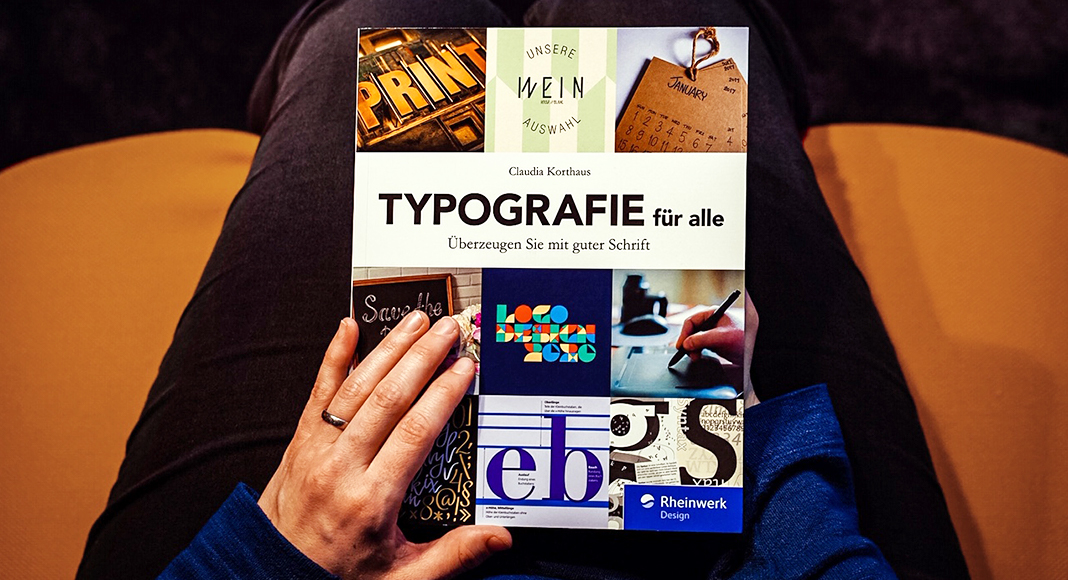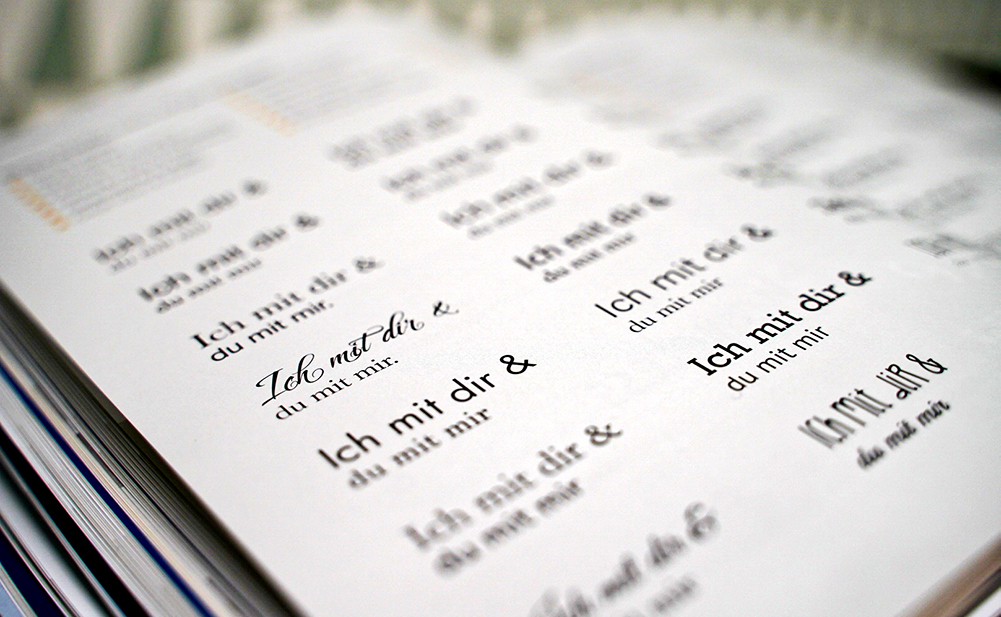
Wir haben das Buch „Typografie für alle – Überzeugen Sie mit guter Schrift“ von Claudia Korthaus gelesen und können es Ihnen auf jeden Fall ans Herz legen. Damit Sie sich einen Überblick verschaffen können, stellen wir Ihnen das Buch im Folgenden vor.
Wenn Sie für die Gestaltung von Drucksachen, Werbemitteln und anderen Designs eine überzeugende Typografie suchen, finden Sie in diesem Ratgeber Antworten. Die Autorin richtet sich mit ihren Tipps bewusst an alle, die im Alltag mit Schrift zu tun, aber Design nicht als Handwerk gelernt haben.
Claudia Korthaus arbeitet als selbstständige Grafikdesignerin, hat bereits mehrere Bücher zum Thema Typografie und Design veröffentlicht und schreibt regelmäßig Fachartikel für das ONLINEPRINTERS-Magazin.
Buchvorstellung: „Typografie für alle“
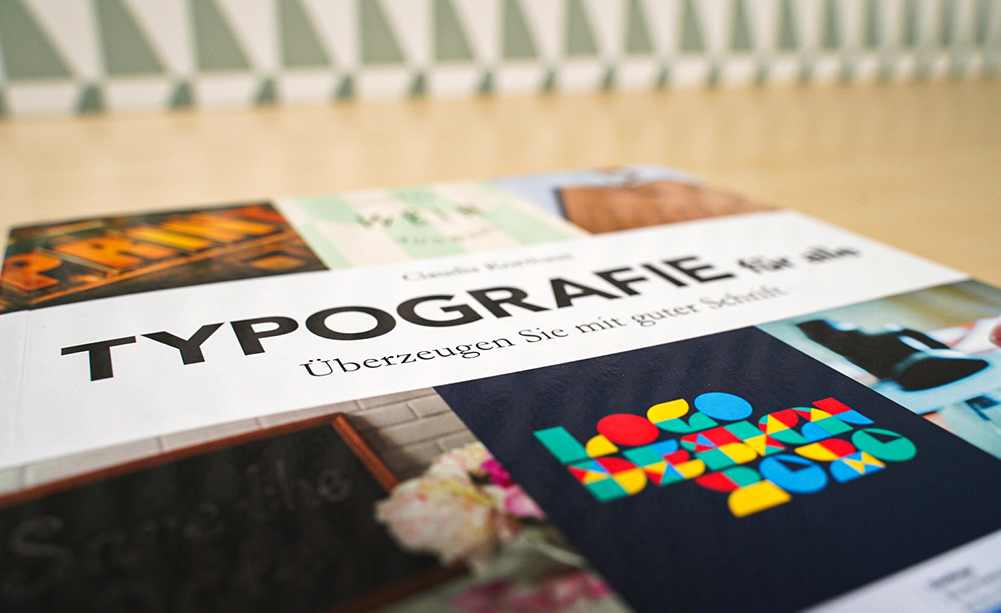
Auf den Innenseiten des Umschlags wird der Leser mit anschaulichen Begriffserklärungen begrüßt. Auch im Rest des Buches gibt es auf den in einem übersichtlichen Layout gestalteten Seiten immer wieder Definitionen zu entdecken. Das erleichtert das Lesen ungemein. Der Text selbst ist das Gegenteil von einer Bleiwüste und weist eine ansprechende Gestaltung auf. Er ist unterbrochen von zusammengefassten Erläuterungen sowie grau hinterlegten Absätzen mit zahlreichen Beispielen oder wissenswerten Exkursen.
„Typografie für alle“ ist in zwei große Teile unterteilt: Theorie und Praxis. Wobei diese Kategorisierung nicht ganz den Kern erfasst, denn auch in der ersten Hälfte finden sich Beispiele aus der Praxis. In den ersten drei Kapiteln erklärt Claudia Korthaus, warum Schriften wichtig sind. Im Zweiten gibt sie einen rechtlichen Abriss über Lizenzen und im Dritten werden Schriftwahl und -Kombinationen zum Thema. In Kapitel vier befasst sich die Designerin mit konkreten Gestaltungsbeispielen und gibt Tipps für den guten Einsatz von Schriften.
Kapitel 1: Die Bedeutung von Typografie
Gute Typografie ist wichtig „für jeden, der über die Schrift einen Inhalt transportieren und diesen zudem noch verständlich darstellen möchte“, wie Claudia Korthaus erklärt. Inhalt und Gestaltung unterstützen sich dabei gegenseitig. Jedes einzelne Zeichen trägt zur Vermittlung der Botschaft bei, während das Gesamtbild mehr ist als die Summe seiner Einzelteile.
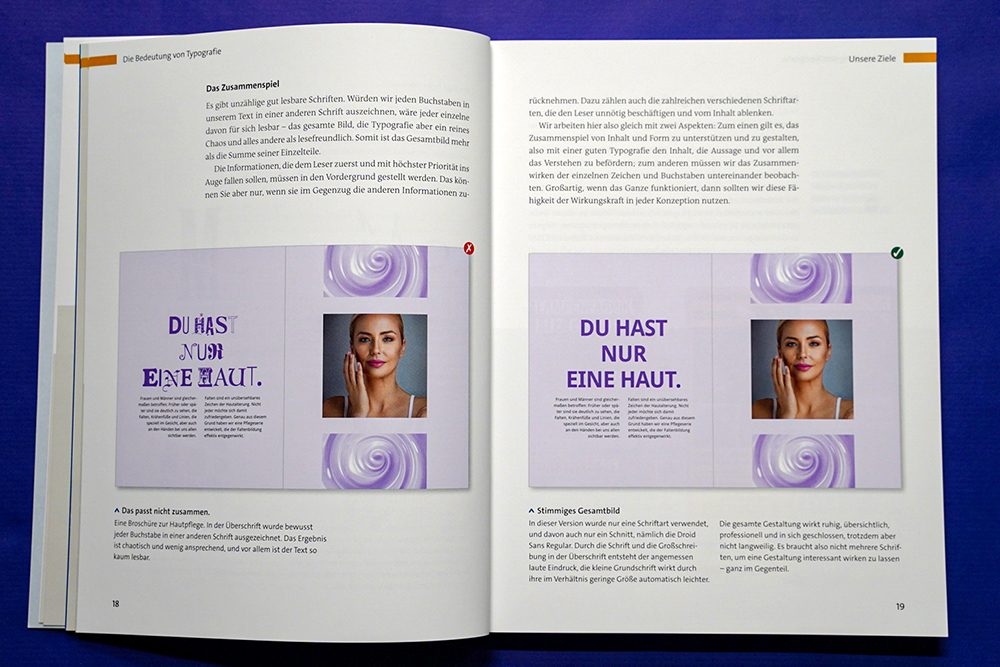
Das veranschaulicht die Autorin in diesem Kapitel mithilfe von Vorher-Nachher-Beispielen. So werden die Ziele, Regeln und Grundsätze der Typografie für Nicht-Designer leicht greifbar.
Kapitel 2: Die Schrift als Schlüssel
Warum wir bei der Gestaltung auf die Typografie achten sollten, wissen wir nun. Im zweiten Kapitel erfahren Leser dann, wo sie passende Schriften für eigene Projekte finden und worauf bei der Beschaffung geachtet werden muss (Stichwort: Lizenzen). Die Qualität von Schriften – bzw. wie man gute erkennt und von schlechten unterscheidet – wird ebenfalls thematisiert.
Listen von Online-Anbietern (mit kostenpflichtigen und kostenlosen Schriften!) ergänzen den theoretischen Teil. Wer sich nicht durch die verschiedenen Schriftarten im Netz wühlen möchte, bekommt eine Empfehlungsliste von Claudia Korthaus an die Hand.
Hier lohnt sich ein Lesezeichen oder ein Haftmarker, denn ebendiese Aufzählungen und Tipps machen „Typografie für alle“ zu einem wertvollen Nachschlagewerk.
Danach geht es weiter mit Schriftdetektiven („Tools zur Schrifterkennung“) und Alternativen zu bekannten Schriften wie Times New Roman, Helvetica oder Arial.
Kapitel 3: Schriftwahl und Schriftmischung
Selten kommt man beim Gestalten mit einer Schrift in einem einzigen Schriftbild aus. Die Kombination macht’s. Doch dabei führt nicht jeder Mix unterschiedlicher Schriften zu einer guten Typografie.
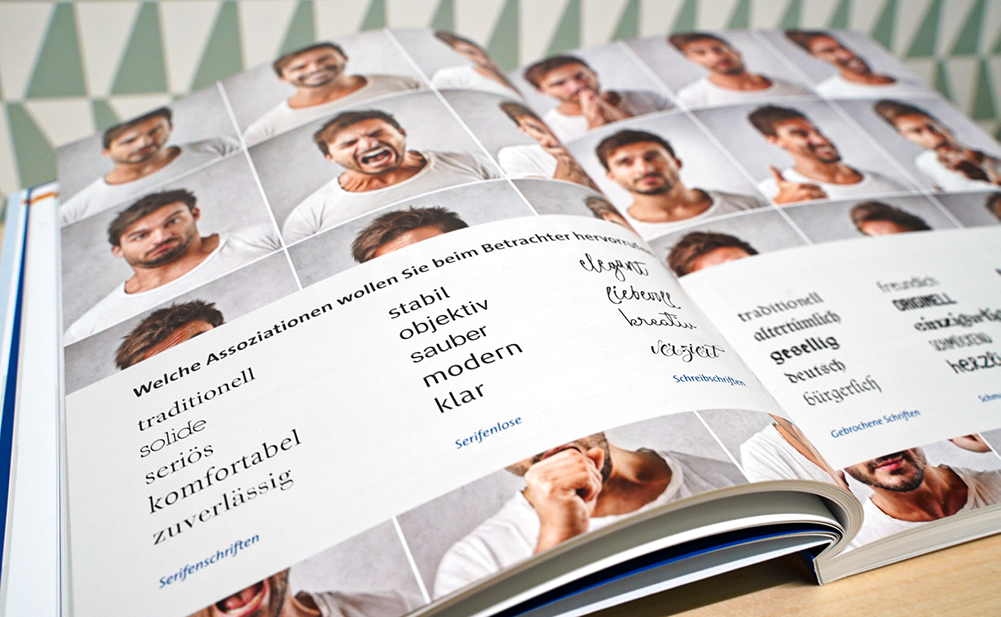
Die Kategorisierung der Schriften in ein Schubladenmodell hilft bei den Regeln fürs Mischen: Claudia Korthaus stellt sechs Schubladen (u. a. Serifenschriften und Schreibschriften) und die Eigenschaften von Schriften in Kästen vor. Damit verknüpft sie deren Lesbarkeit und stellt die Wirkung der verschiedenen Schrifttypen heraus – woraus sich unterschiedliche Einsatzgebiete und Tabus ergeben.
Besonderes Augenmerk legt die Autorin dabei auf Schriftmischungen. Ab Seite 108 finden sich Praxistipps dazu.
Kapitel 4: Die Praxis
In der zweiten Hälfte des Buches erläutert Claudia Korthaus anhand von acht einschlägigen Beispielen, wie man die Grundsätze der Typografie in unterschiedlichen Arten der Gestaltung anwenden kann. Eine Einladung darf beispielsweise mit einem auffälligen Font aufwarten. Die Schrift in einem Bericht indes sollte gut lesbar, die Gestaltung darin klar sein.
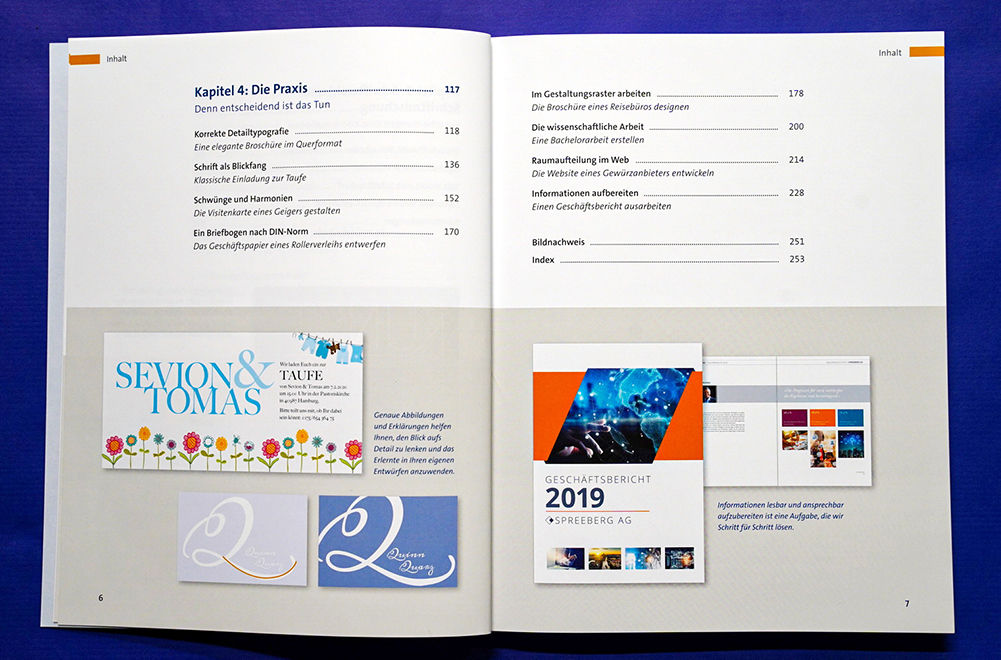
Diese konkreten Anwendungsbeispiele dienen als Hilfestellung, fast sogar als Anleitung. Und auch, wenn der Leser sein eigenes Projekt nicht eins zu eins in den Beispielen wiederfindet, lassen sich daraus wichtige Hinweise und Tipps ablesen. Dabei werden weitere wertvolle Hintergrundinformation zu Typografie und Gestaltung anschaulich vermittelt – Orthografie, DIN-Vorgaben, Satzspiegel oder Textausrichtung.
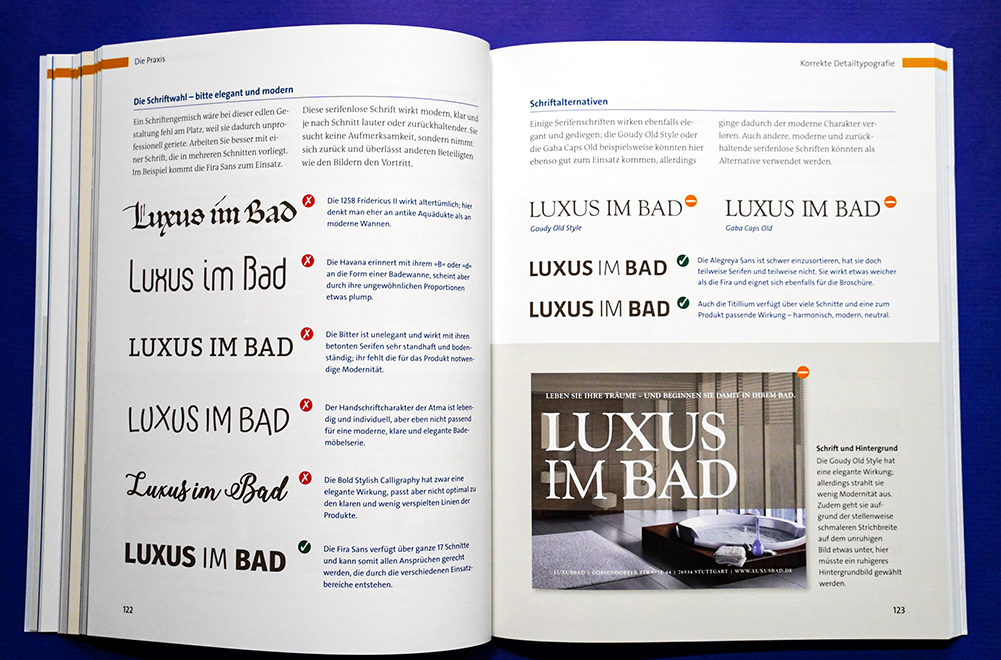
Highlights
Zu den Höhepunkten von „Typografie für alle“ zählen vor allem die hilfreichen Listen, die Autorin Claudia Korthaus zur Verfügung stellt. Damit wird der lesenswerte Ratgeber zu einem informativen Nachschlagewerk. Der Blick ins Buch kann sich vor jeder neuen Gestaltung lohnen.
Listen
- Schriftportale mit kostenlosen Schriften, Seite 35
- Schriftportale mit kostenpflichtigen Schriften, Seite 37
- Internetseiten zum Thema Typografie: Fundstücke und Inspiration; Seite 38
- Serifenlose Schriften, Serifenschriften, Schreib- und Schmuckschriften sowie gebrochene Schriften und Stilschriften, ab Seite 46
- Schriftdetektive, Seite 53
- Alternativen zu bekannten Schriften (Times, Verdana, Helvetica und Arial), ab Seite 54
- Liste mit Negativ-Top-21, Seite 63
- Beispiele: Welche Assoziationen wollen Sie beim Betrachter hervorrufen? ab Seite 76
- Schriftwirkung verschiedener Schriften mit unterschiedlicher Strichstärke, ab Seite 86
- Checkliste: So erhöhen Sie die Lesbarkeit, Seite 106
- Gute Schriftmischungen, ab Seite 114
Im zweiten Teil des Buches warten blau hinterlegte Blöcke auf die Leser, in denen die Autorin kurz über wissenswerte Themen zur Gestaltung mit Schrift bzw. Text informiert. Diese Sektionen, von der Autorin „Genauer betrachtet“ genannt, bieten sich auch für das ein oder andere Lesezeichen an.
Genauer betrachtet:
- Mikrotypografie und Orthografie, ab Seite 127
- die Bindung – wie halten die Seiten zusammen? Seite 134
- Papier – die Haptik entscheidet mit, Seite 135
- verschiedene Zahlenarten, Seite 146
- Zahlen übersichtlich gestalten, ab Seite 147
- das typografische Maßsystem und das Geviert, ab Seite 164
- Veredelung, Haptik und Wirkung, ab Seite 168
- der Briefbogen nach DIN-Vorgaben, ab Seite 172
- Wege zum Satzspiegel, ab Seite 180
- die Textausrichtung, ab Seite 186
- die Silbentrennung, Seite 189
- Umbruchfehler, ab Seite 206
- Diagramme und Tabellen, ab Seite 209
- Schriftregeln im Web, Seite 223
- die richtige Schriftgröße für Print und Web, ab Seite 224
- die Zeilen- bzw. Spaltenbreite und der Spaltenzwischenraum, ab Seite 232
- das Zeilenraster für registerhaltigen Text, Seite 234
- Zwischenüberschriften und Abstände, ab Seite 242
- das Inhaltsverzeichnis, ab Seite 246
Schrift: The AntiquaB 9,35 Pt. (Serifenschrift)